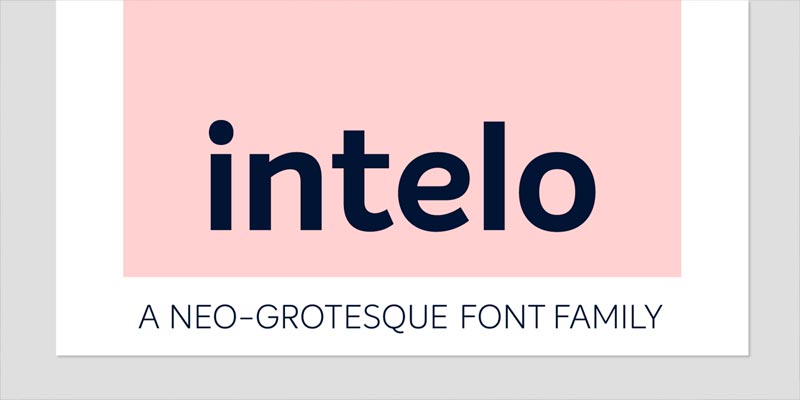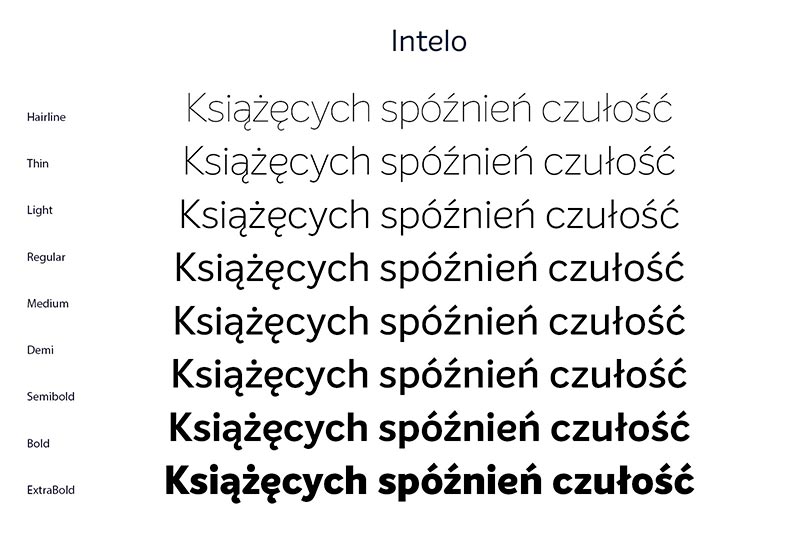
Font Intelo
Do naszego studia graficznego trafił nowoczesny font Intelo, zaprojektowany w 2016 roku przez Galina Kastelova z Bułgarii. Zestaw składa się z 8 odmian grubości wraz z italikami oraz wersje alternatywne. Intelo to bezszeryfowy font o humanistycznym charakterze.